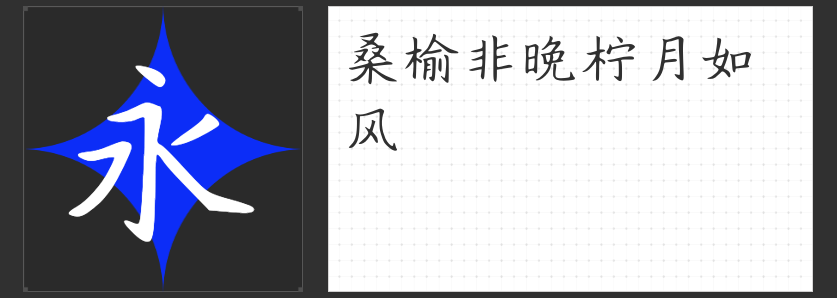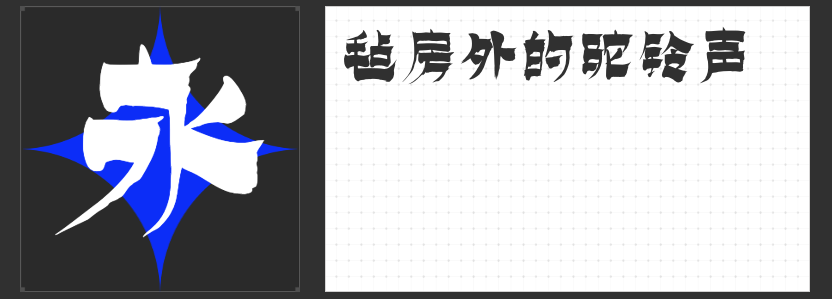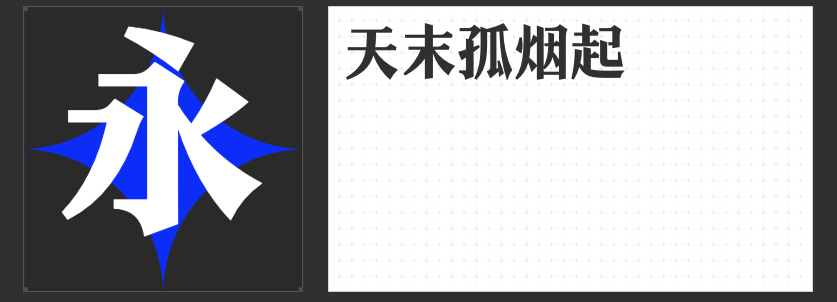
怀旧风情,字体推荐:四款古风韵味十足的字体
在追求现代设计感的同时,怀旧风格的设计元素也悄然回归,成为一股不可忽视的潮流。字体作为设计的重要组成部分,其风格直接影响着整体设计的氛围。今天,为大家推荐四款充满古风韵味的怀旧字体,它们不仅各具特色,还能为设计增添一抹独特的文化气息。
一、云书法三行魏碑体
这款字体以工整的楷书为基底,整体字形柔和流畅,颇具古风韵味。笔划严谨朴厚,灵动而不失力度,展现出朴拙险峻、舒畅流丽的美感。无论是用于标题还是正文,都能为文本增添一份古朴典雅的气质,让人仿佛穿越回千年前的书卷世界。
这是一款极具创意的毛笔手书字体,笔画厚重有力,撇字清晰从容,展现出独特的灵性。框架醒目,字型端庄,字体风格统一,非常适合用于包装印刷、广告设计以及平面设计等领域。其独特的漆书风格,让人一眼难忘,为设计作品增添一份独特的艺术魅力。
这款行书字体笔画窈窕秀丽,结构洒脱自然,用笔圆融流畅。每个字中都有一画或多画点睛之笔,使字形更加饱满生动。其独特的风格不仅适用于书法爱好者,还能为设计作品增添一份灵动与飘逸。
四、字圈也字山海明朝
字圈也字山海明朝在黑体架构上融入了宋体的衬角装饰,经过大量优化,呈现出大气、端正且富有趣味性的视觉效果。这款字体既保留了黑体硬朗的转折特点,又融入了宋体柔美的书写特征,使整体风格更加协调统一。无论是用于标题字还是正文排版,都能展现出其独特的魅力。
这四款字体各具特色,都能为设计作品增添一份独特的文化气息和怀旧风情。选择一款适合自己的字体,让设计作品更加出彩吧!